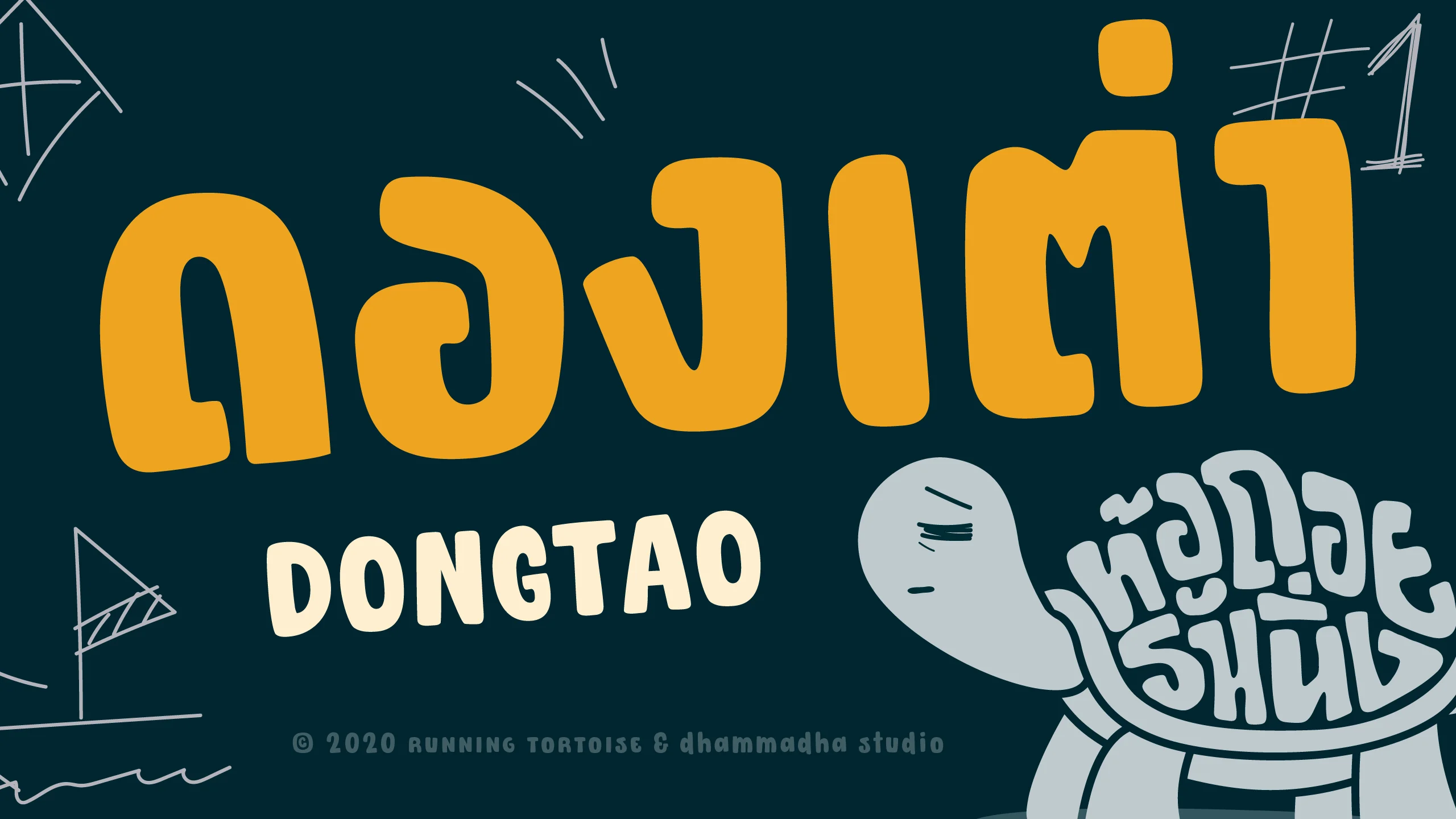
"ดองเต่า | DONGTAO" คือชุดอักษรพาดหัวที่มีจุดเริ่มต้นมาจากมิตรภาพและความสนุกสนานในเพจ "ท้อถอยรันนิ่ง / RUNNING TORTOISE" โดยหยิบเอาลายเส้นอันเป็นเอกลักษณ์จากโลโก้เพจมาพัฒนาสู่ฟอนต์ที่สะท้อนบุคลิกเป็นกันเองและดูมีชีวิตชีวา ฟอนต์ชุดนี้เปี่ยมไปด้วยเสน่ห์ที่ดูเท่และเก๋ไม่ซ้ำใคร แฝงไว้ด้วยเรื่องราวการเดินทางและการพักผ่อนที่เรียบง่ายแต่เป็นกันเอง เหมาะอย่างยิ่งสำหรับงานออกแบบที่ต้องการส่งต่อพลังบวกและความสนุกสนานให้กับผู้พบเห็น สอดแทรกกลิ่นอายความผ่อนคลายที่ทำให้งานดีไซน์ดูเข้าถึงง่ายและเป็นมิตรกับทุกคน ด้วยรูปลักษณ์ที่ดูหนาแน่นและมีจังหวะที่สนุกสนาน "ดองเต่า | DONGTAO" จึงออกแบบมาเพื่อเป็นฟอนต์พาดหัวที่สร้างความโดดเด่นให้กับทุกชิ้นงาน ไม่ว่าจะเป็นคอนเทนต์สายท่องเที่ยว สายกีฬา หรือแม้แต่งานกราฟิกที่ต้องการความขี้เล่นและดูไม่เป็นทางการจนเกินไป นอกจากจะช่วยยกระดับงานดีไซน์ให้ดูมีสไตล์แล้ว ส่วนหนึ่งของการสนับสนุนฟอนต์ชุดนี้ยังเปรียบเสมือนการร่วมส่งต่อแรงบันดาลใจ (และกำลังใจในรูปแบบของหมูกระทะ) ให้กับการขับเคลื่อนโปรเจกต์สนุกๆ ต่อไปในอนาคต ทำให้ทุกตัวอักษรของดองเต่าไม่ได้มีเพียงแค่ความสวยงาม แต่ยังมีเรื่องราวของรอยยิ้มและความจริงใจแฝงอยู่ในทุกรายละเอียด ต้นแบบโดย : RUNNING TORTOISE พัฒนาฟอนต์โดย : Montonn Thanaroj